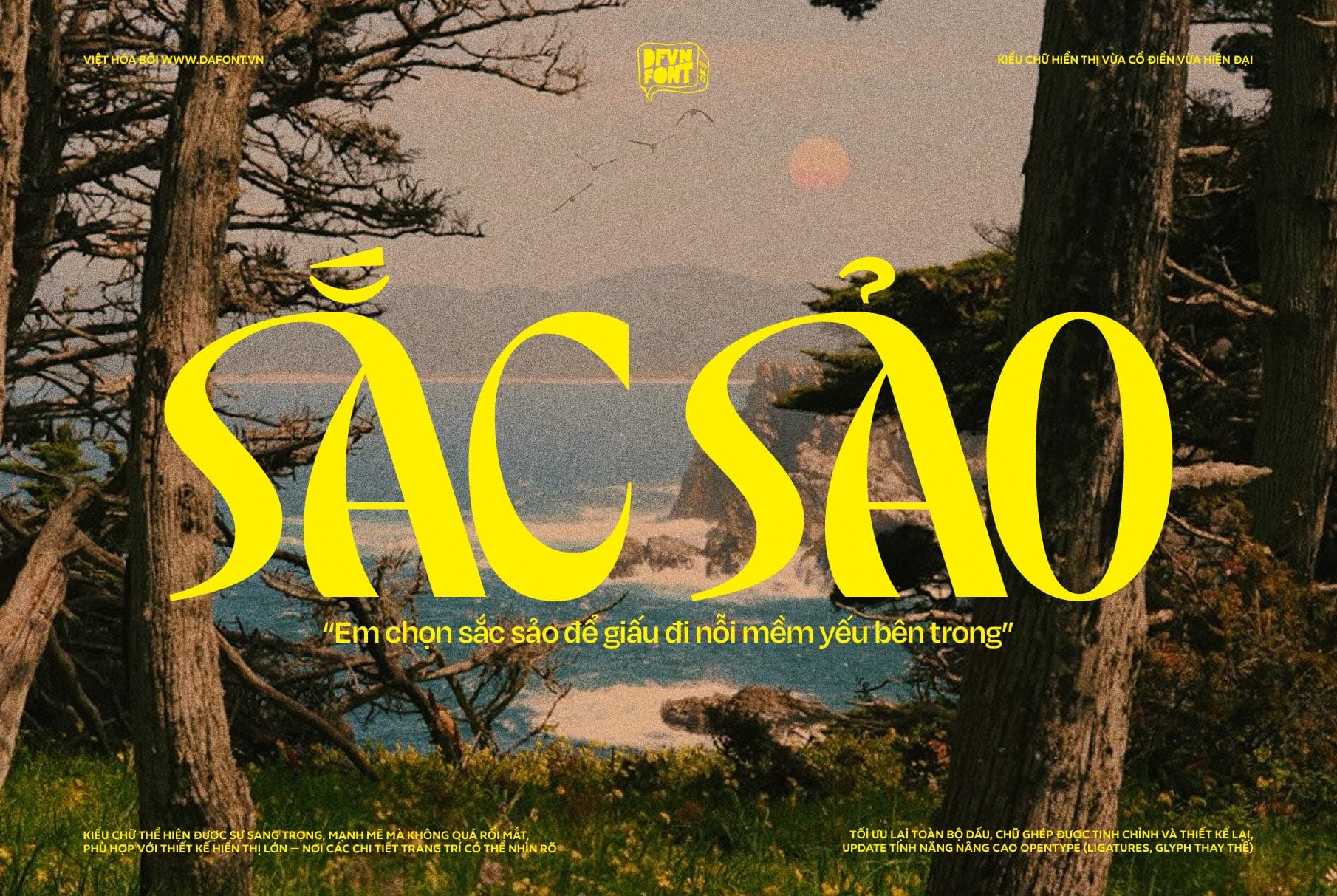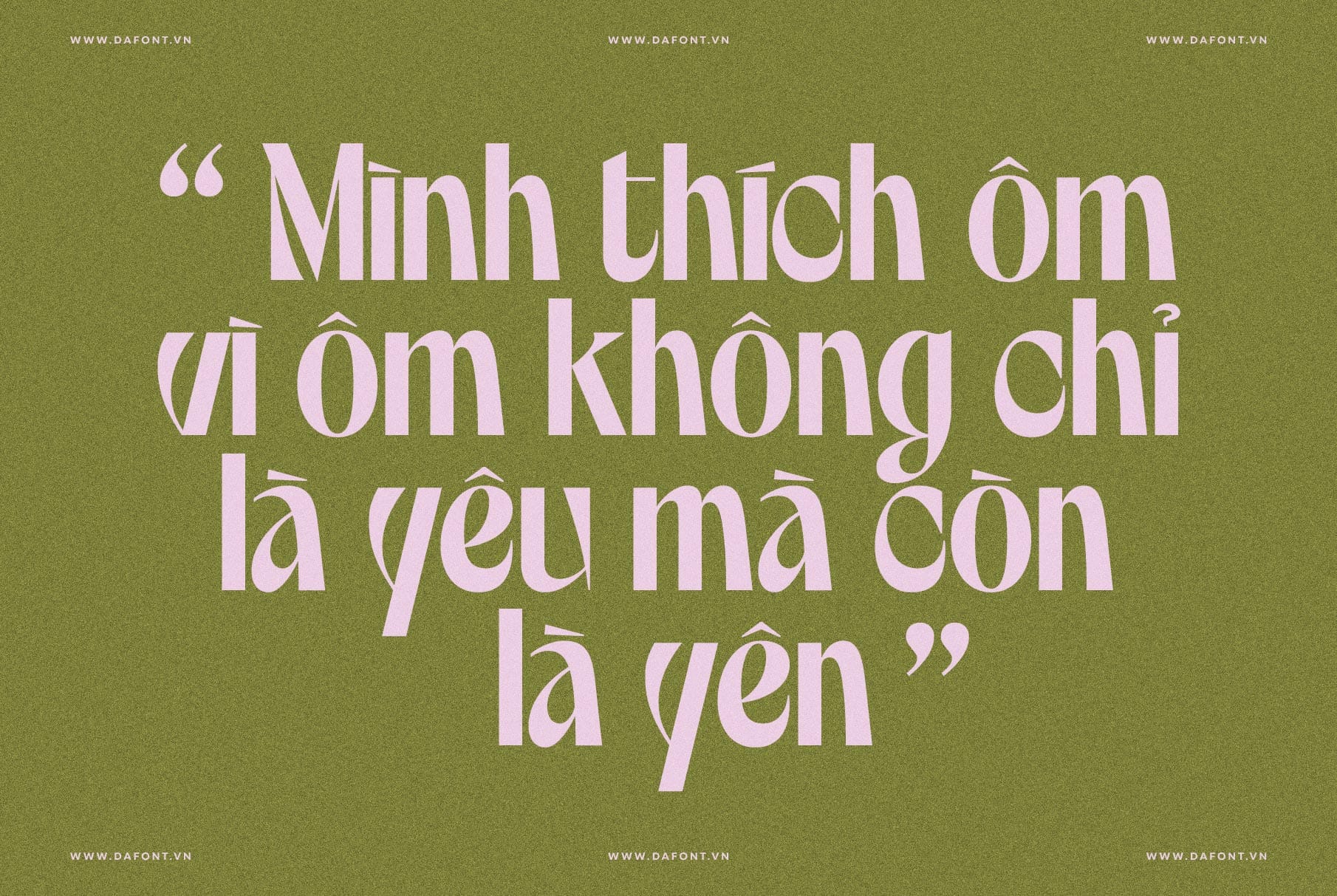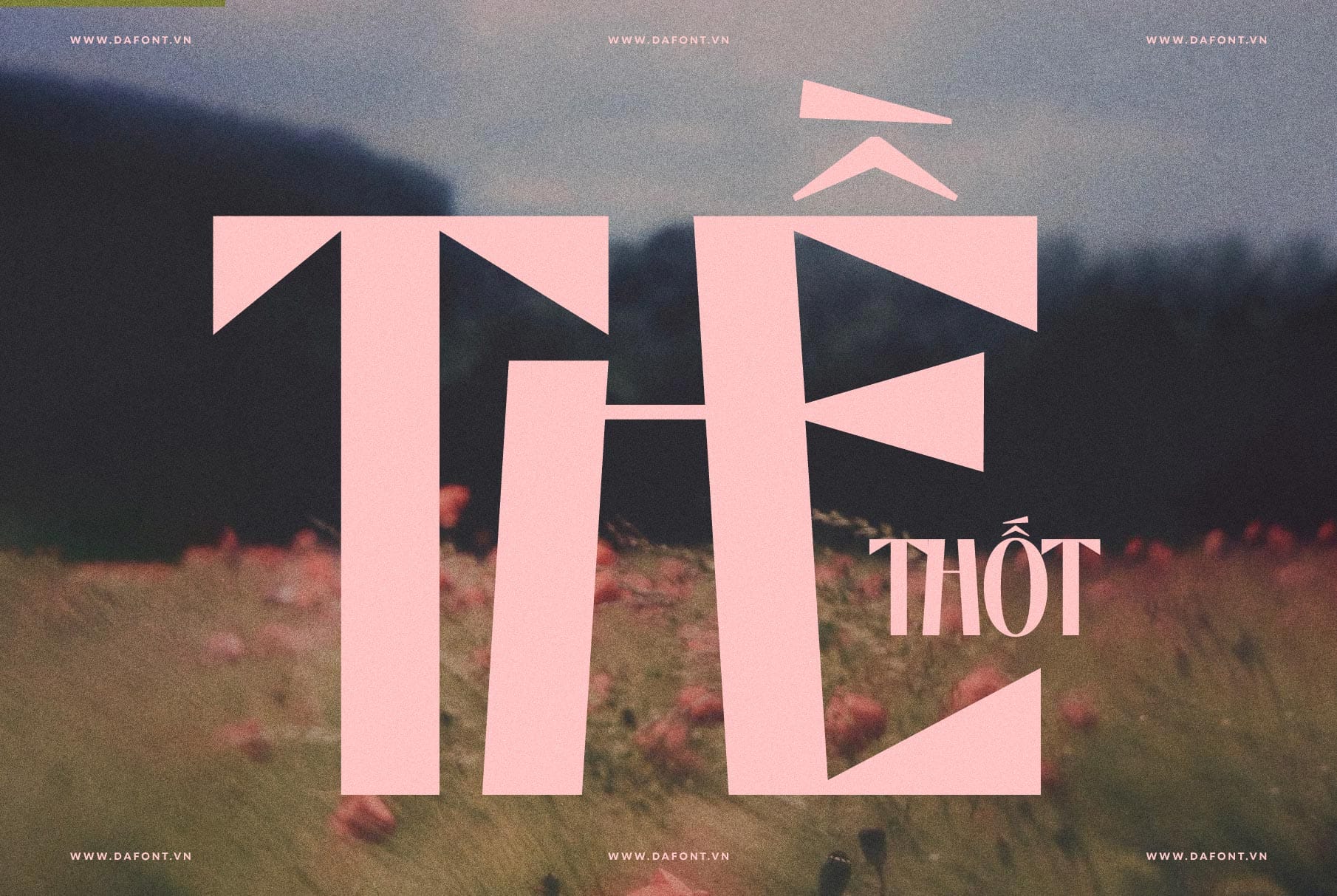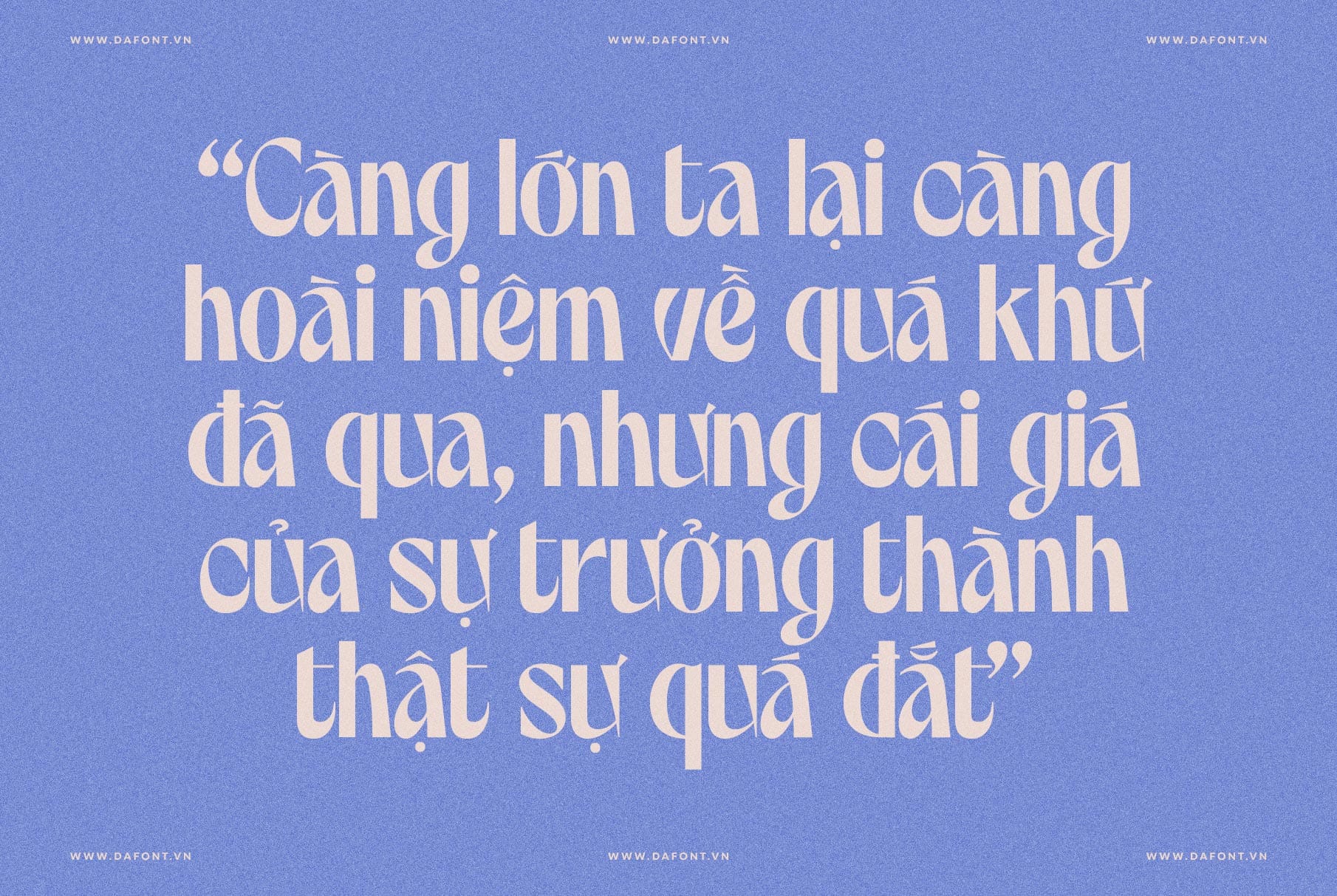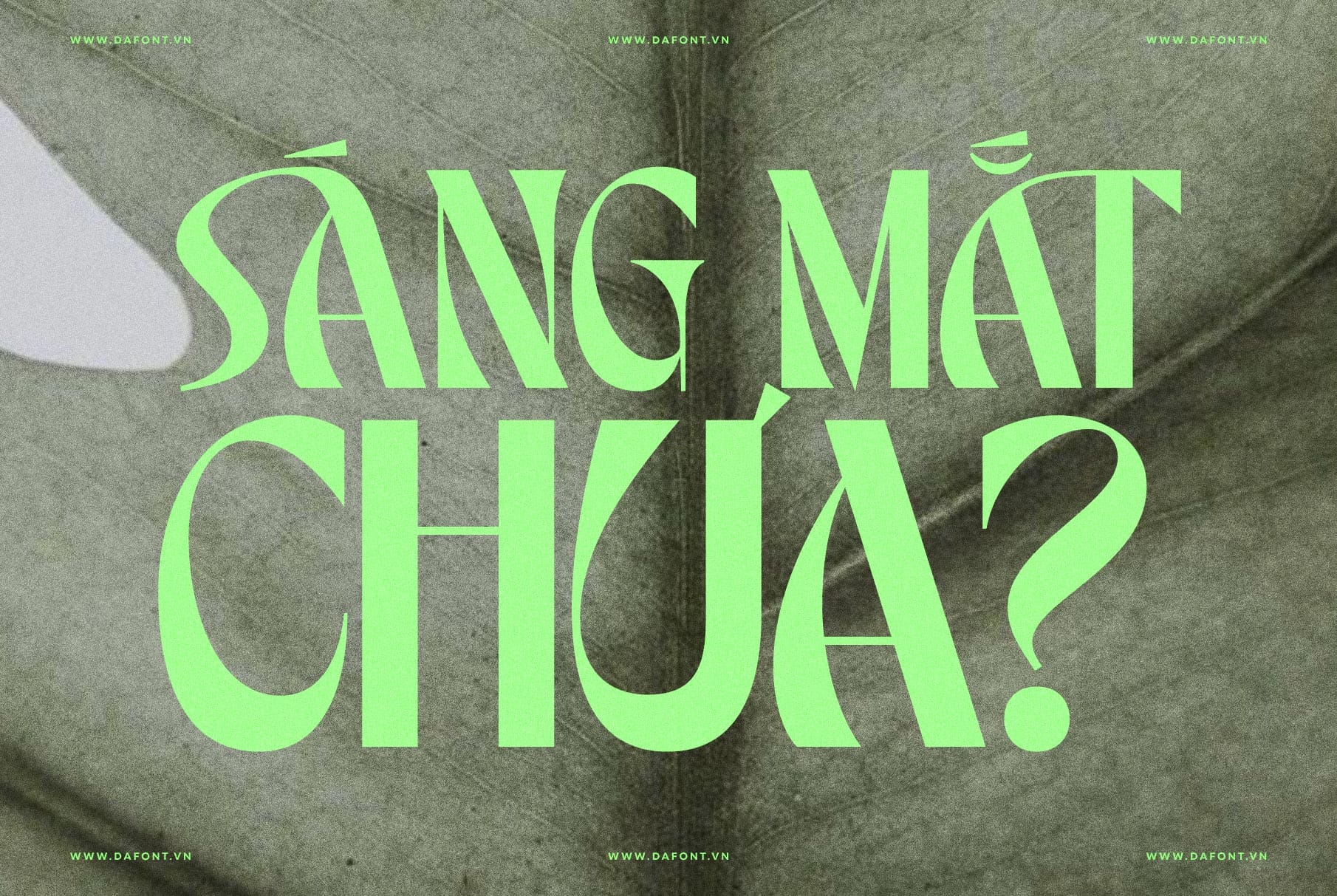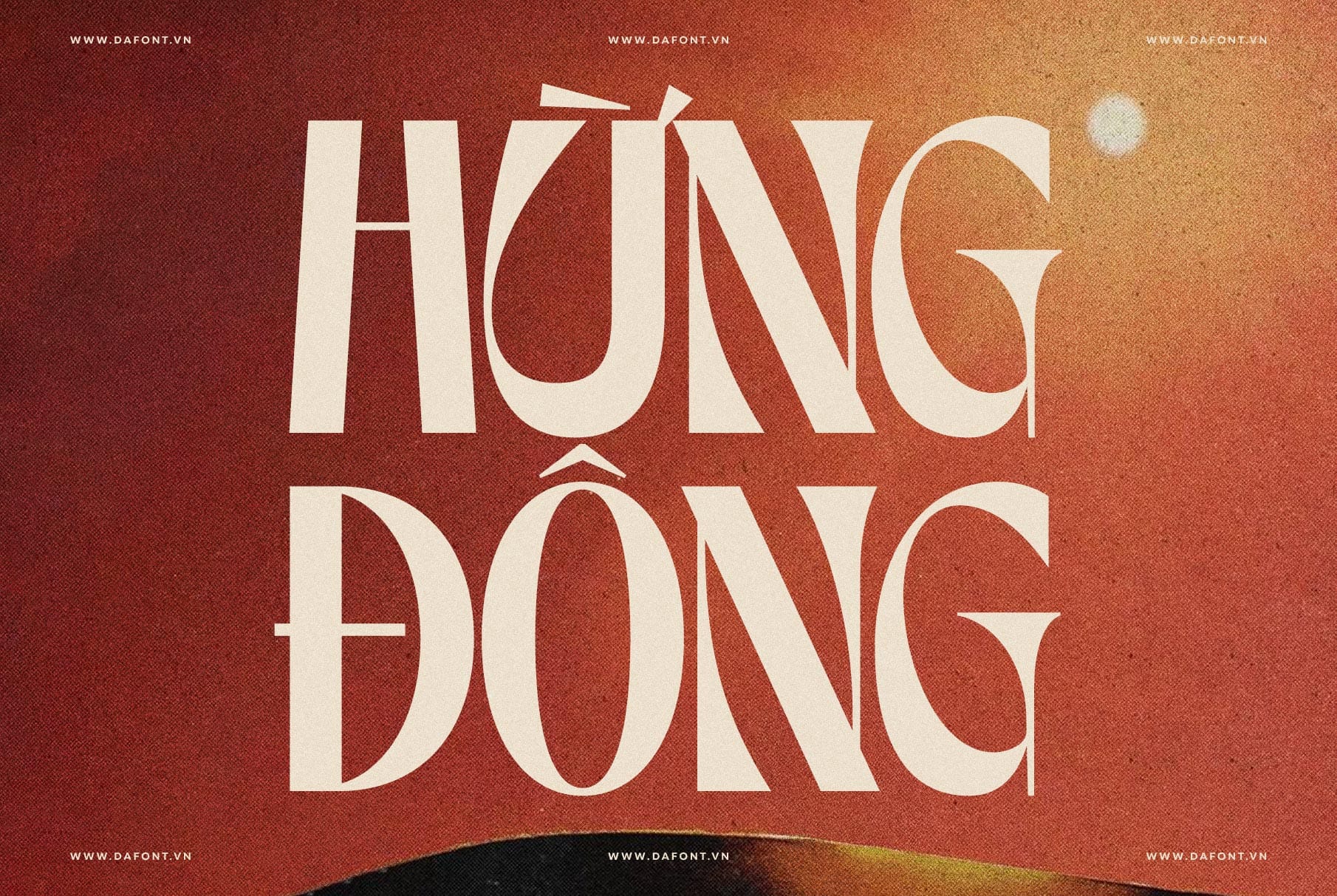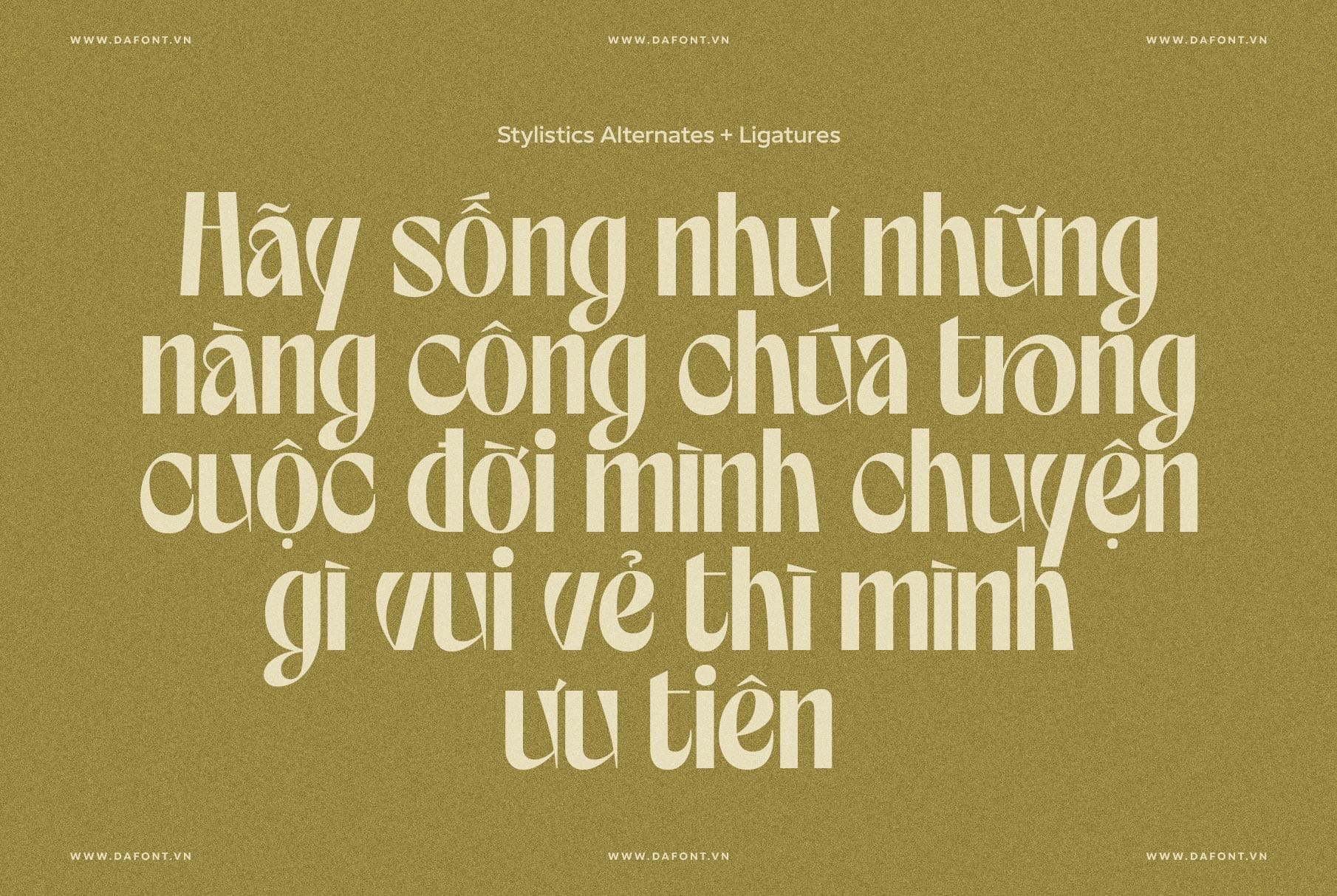
DFVN TAN – SALTERS là một font hiện đại, nổi bật với phong cách đậm nét, thanh lịch và mang hơi hướng thiết kế giữa thế kỷ 20 (midcentury) đặc trưng bởi những đường nét gọn gàng, đơn giản và không cầu kỳ. Đây là một font thuộc nhóm display (trang trí/tiêu đề), nghĩa là nó được thiết kế chủ yếu để sử dụng ở kích thước lớn như tiêu đề, logo, poster, branding, thay vì dùng cho đoạn văn bản dài.
Đặc điểm nổi bật DFVN TAN – SALTERS
DFVN TAN – SALTERS là một typeface display mang vẻ đẹp vượt thời gian, kết hợp hài hòa giữa tinh thần mid-century cổ điển và phong thái hiện đại. Font tạo nên cảm giác sang trọng, cân đối nhưng vẫn giữ được sự gần gũi – lý tưởng cho các thiết kế sáng tạo, editorial, và nhận diện thương hiệu. Dưới đây là những điểm nổi bật đáng chú ý:
- Phong cách mid-century pha hiện đại: Đường nét tinh gọn, tỷ lệ hài hòa, gợi cảm giác sang trọng nhưng nhẹ nhàng; hoàn hảo cho tiêu đề và thiết kế mang hơi hướng retro tinh tế.
- Tạo ấn tượng mạnh ở kích thước lớn: Là một display typeface, DFVN TAN – SALTERS thể hiện độ hiện diện mạnh mẽ khi dùng cho headline, poster, bao bì hoặc key visual.
- Retro-modern cân bằng: Giữa mềm mại và vững chắc, font truyền tải tinh thần hoài cổ nhưng không lỗi thời – vừa cổ điển vừa đậm chất đương đại.
- Hỗ trợ ligatures và alternates: Bổ sung chữ ghép và ký tự thay thế giúp tạo nhịp điệu chữ riêng, mang lại cảm giác chuyển động tự nhiên trong bố cục.
- Kerning tinh chỉnh tỉ mỉ: Tất cả ký tự được cân chỉnh khoảng cách tối ưu, đảm bảo bố cục tiêu đề hoặc logotype luôn hài hòa và dễ đọc.
- Hỗ trợ mã PUA đầy đủ: Giúp bạn dễ dàng sử dụng toàn bộ glyph và ký tự đặc biệt trên mọi phần mềm như Word, Figma hay Canva – ngay cả khi không bật tính năng OpenType.
Đề xuất sử dụng DFVN TAN – SALTERS trong thiết kế
- Branding & bao bì cao cấp: Phù hợp cho wordmark, nhãn hàng hoặc hệ thống tiêu đề nhận diện thương hiệu.
- Editorial, poster & key visual: Dành cho headline, sub-headline hoặc layout cần điểm nhấn retro-modern cuốn hút.
- Bìa ấn phẩm & video title cards: Thích hợp cho thiết kế cần ấn tượng thị giác mạnh, dễ đọc và có nhịp chữ sinh động nhờ ligatures.
- Ưu tiên sử dụng cho tiêu đề ngắn hoặc cụm chữ lớn; tránh áp dụng cho đoạn văn nhỏ vì là display font.
- Tận dụng mã PUA để truy cập nhanh các glyph đặc biệt trên Canva, Figma hoặc Word; thử nghiệm nhiều cặp chữ để tạo bố cục nhịp nhàng và độc đáo.
Việt hóa tỉ mỉ, chăm chút từng chi tiết
DFVN TAN – SALTERS được Việt hóa hoàn chỉnh với kerning toàn bộ ký tự, bao gồm cả chữ ghép và chữ cái thay thế. Phiên bản này bổ sung hơn 200 glyph mới, mang đến các chữ ghép siêu đẹp có thể kích hoạt dễ dàng thông qua tính năng OpenType.
Ngoài ra, font cũng hỗ trợ mã PUA đầy đủ, cho phép bạn sử dụng toàn bộ ký tự trên mọi nền tảng – từ Word, Figma đến Canva – mà không bị giới hạn bởi khả năng hỗ trợ OpenType của từng phần mềm.